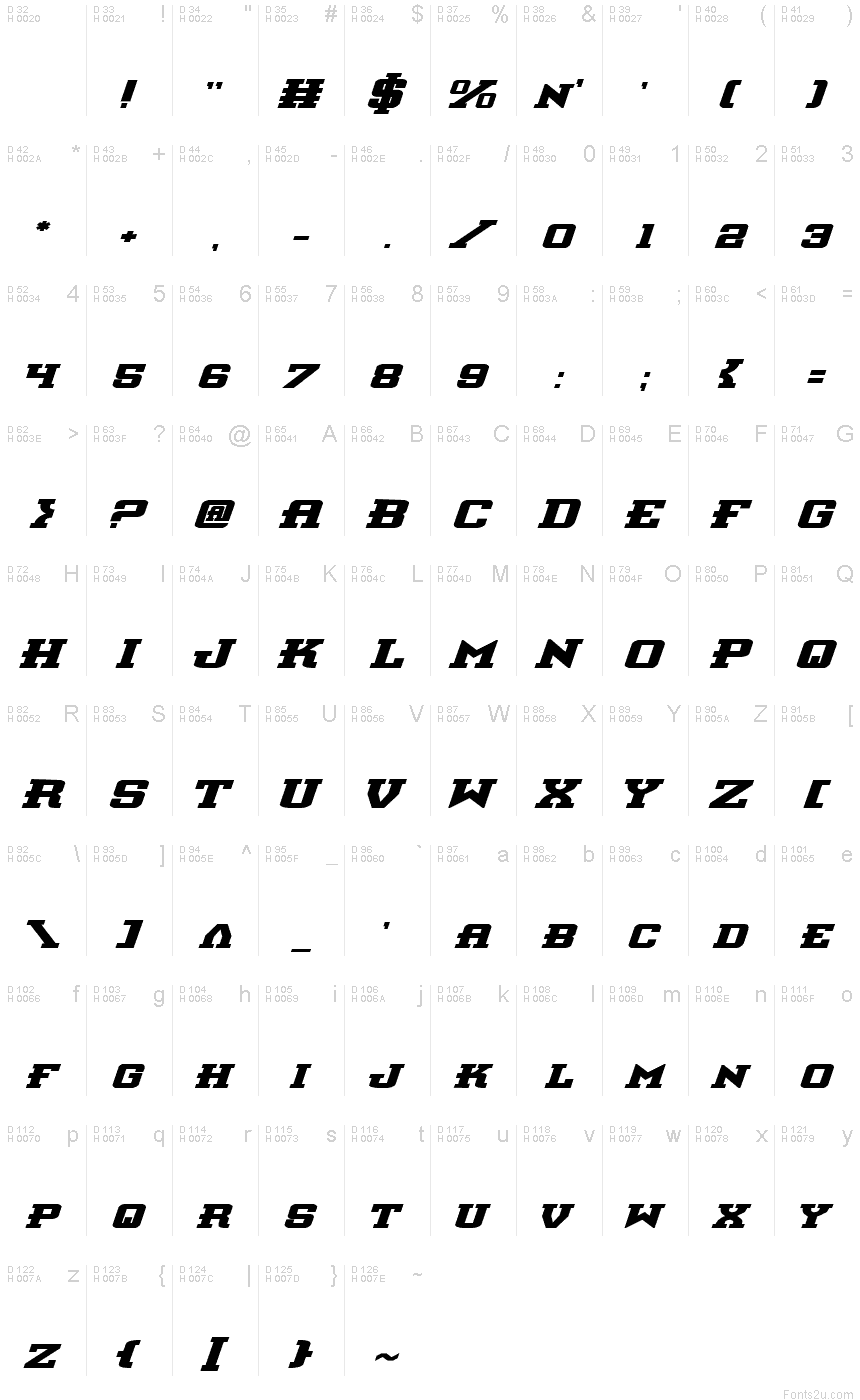
Interceptor von Iconian Fonts ist eine kostenlose, futuristische Display-Schrift mit der Dynamik eines Rennstreifens. Die Buchstaben neigen sich nach vorne und verleihen dem Schriftbild durch ihre breiten, kantigen Silhouetten und scharfen, treppenartigen Schnitte einen schnellen, mechanischen Rhythmus – wie aus einem Sci-Fi-Blockbuster oder klassischen Arcade-Titeln.
Die Schrift eignet sich hervorragend für Gaming-Logos, Plakate, Albumcover, Titeltafeln und Team-Branding, wo dieser kostenlose Font allein durch seine Form kurze Schriftzüge zum Strahlen bringt. Setzen Sie ihn überall dort ein, wo Buchstaben in Bewegung wirken sollen – ideal für Überschriften, Monogramme oder kompakte Wortmarken, die von der aggressiven, geneigten Haltung profitieren.
Interceptor Bold ExpItalic